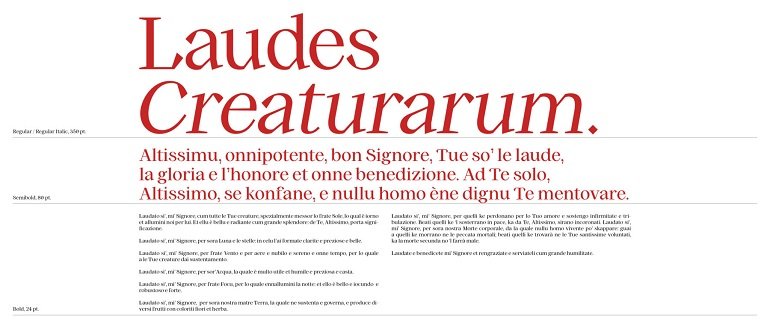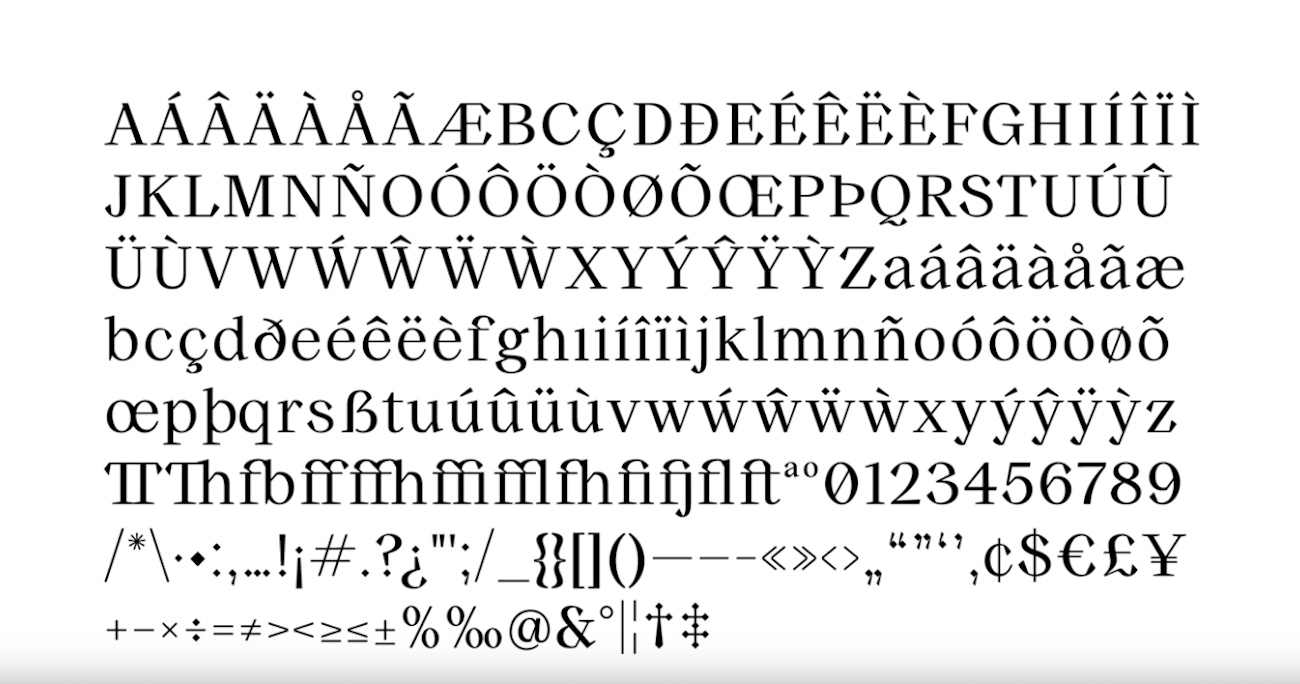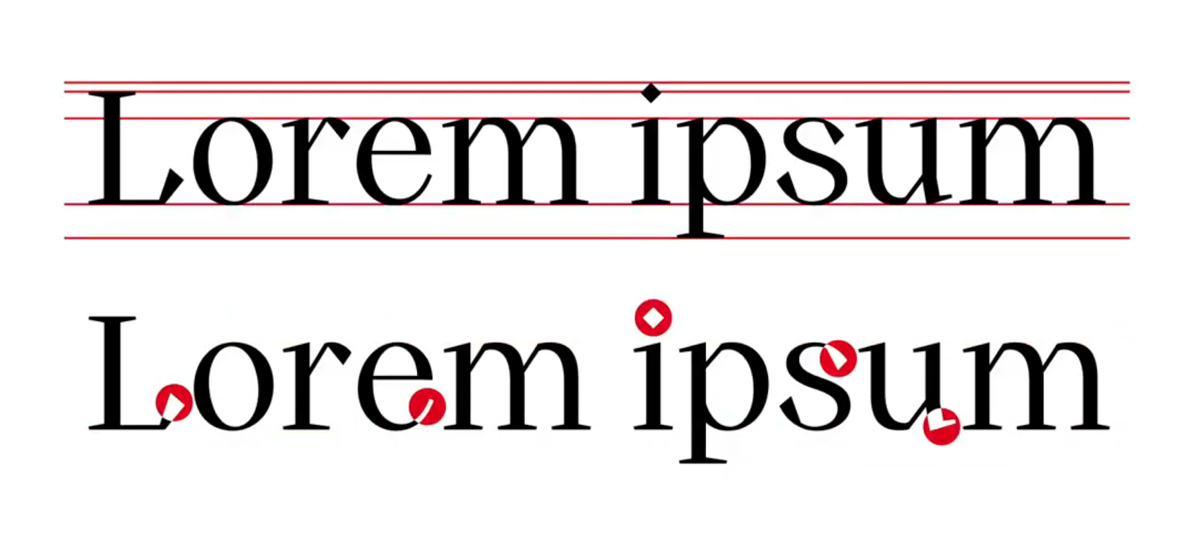
Franciscus è il primo font ufficiale della Chiesa Cattolica, realizzato dai frati di Assisi e ispirato, ovviamente, a San Francesco d’Assisi. Spigoloso, come i caratteri godici medievali, rosso come le parole scritte dagli amanuensi, ma con un pizzico di moderno perché, come ricordano i frati francescani, le parole del Santo d’Assisi sono sempre attuali.
La nascita del font Franciscus
Franciscus è il font elaborato dai frati della basilica di San Francesco in collaborazione con i designer di Studiogusto. Per realizzarlo hanno tratto ispirazione dai manoscritti che vanno dal ‘200 al ‘400, che sono conservati all’interno della Biblioteca del Sacro Convento.
Trae anche ispirazione dagli affreschi presenti nella Basilica di San Francesco. Nonché dalle parole scritte dal Santo di suo pugno, nella Chartula di Assisi.
Il font sembra provenire da un’altra epoca. È così tanto old style che sembrerebbe non addirsi affatto a un’epoca moderna. Ma c’è quel tocco di new school a fare la differenza. I designer e i frati francescani sono infatti partiti da un filo comune per realizzare il font, con l’intento di coniugare la tradizione con il contemporaneo.
Franciscus si rifà all’epoca di San Francesco, affonda le sue radici nel tredicesimo secolo, per affacciarsi al mondo moderno, digitalizzando la chiesa stessa.
Com’è fatto Franciscus?
Franciscus è spigoloso, ma anche curvo e delicato. È rosso e dai bordi geometrici. Franciscus è il dualismo. Sì, perché in esso racchiude il passato di San Francesco e il presente dei frati francescani odierni. Il tradizionalismo della chiesa cattolica e il digitale della vita odierna. Per avvicinare mondi lontani e trovare una connessione.
Franciscus è spigoloso come i caratteri gotici medievali dai quali trae ispirazione. Ma ha anche delle curve più delicate, accompagnate dai bordi geometrici. Tutto ciò lo rende estremamente adattabile ad ogni contesto. Dà il suo meglio adattandosi alle dimensioni del titolo, ma anche con quelle più ridotto del corpo del testo.
Nel complesso, non è “pesante” come i font gotici medievali, e si adatta bene alla lettura, rimanendo anche di bella presenza.
Il font è idealmente rosso, anche se il colore, ovviamente, è a libera scelta.
Ma il colore rosso ha un suo significato per i suoi creatori. Esso, infatti, è il colore con cui gli amanuensi segnalavano l’inizio dei brani, le note o le parti da non leggere ad alta voce, ma che costituivano indicazioni fondamentali.
Ma non dimentichiamoci quel pizzico di contemporaneità, fortemente voluto dai suoi realizzatori. Quello è proprio ciò che ci vuole per ribadire il messaggio di San Francesco. Come si legge dal comunicato stampa, infatti, “il messaggio del Santo d’Assisi è sempre attuale e per restituire all’identità francescana la capacità di rinnovarsi, di aprirsi all’altro. E così sia”.
Ecco il primo font della chiesa
Franciscus è stato realizzato per festeggiare i 100 anni del mensile San Francesco, il quale sarà proprio il primo ad utilizzarlo. Inoltre, anche il sito sanfrancesco.org è tra i primi fruitori del nuovo font. Sul sito ci sarà un forte richiamo al colore rosso, fondamentale, come dicevamo prima.
“Questo nuovo font è un contributo frutto dell’impegno i questi anni del mondo della comunicazione e della ricerca. Segnerà sicuramente una svolta culturale nel digitale. Ed è con lui che scriveremo nuove pagine di vita”, commenta Padre Enzo Fortunato, direttore della Sala Stampa di Assisi.